디자인은 폰트 하나가 아니라 제목과 본문의 관계에서 완성됩니다. 그런데 하나를 고르는 것보다 둘을 짝짓는 편이 훨씬 어렵습니다. 실패하는 조합에는 공통점이 있습니다.
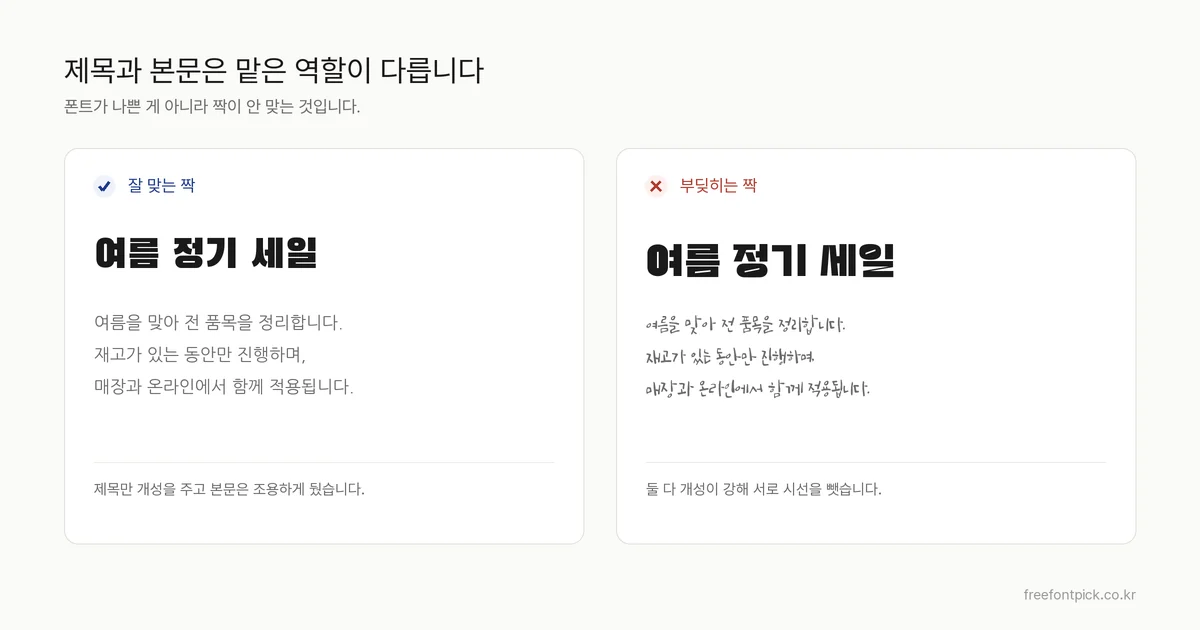
1. 굵기 차이가 모자랄 때
가장 흔한 실패입니다. 제목과 본문이 둘 다 700이면 어느 쪽을 먼저 읽어야 할지 알 수 없습니다. 제목을 더 올리기보다 본문을 400이나 300으로 내리는 편이 대개 낫습니다. 화면이 무거워지지 않으면서 위계가 생깁니다.
2. 개성이 강한 서체를 둘 이상 쓸 때
손글씨와 장식체는 한 자리에만 두고, 나머지는 받쳐 주는 역할로 두세요. 둘 다 튀면 서로를 잡아먹습니다. 제목이 손글씨라면 본문은 담백한 고딕이 좋습니다.
3. 본문에 제목용 서체를 쓸 때
획이 굵고 자간이 좁은 서체는 크게 쓸 때 좋지만, 작게 여러 줄을 쌓으면 글자가 서로 붙어 읽기 어려워집니다. 제목용으로 소개된 폰트는 그 말대로 제목에만 쓰세요.
4. 획 대비가 서로 다를 때
가로획과 세로획의 굵기 차이를 획 대비라고 합니다. 대비가 뚜렷한 명조와 대비가 거의 없는 고딕을 나란히 두면 서로 다른 시대의 글자처럼 보입니다. 반대로 이 차이를 일부러 크게 벌리면 제목과 본문이 확실히 갈라져 보이기도 합니다. 우연히 어긋나는 것과 일부러 벌리는 것은 다릅니다.
5. 같은 집안에서 고르면 안전합니다
가장 실패가 적은 방법은 굵기가 여러 개인 폰트 하나를 골라 제목에 굵은 것, 본문에 가는 것을 쓰는 것입니다. 어울리지 않을 수가 없습니다. 다만 인상이 단조로워지므로, 개성이 필요한 작업이라면 다른 집안에서 짝을 찾으세요.